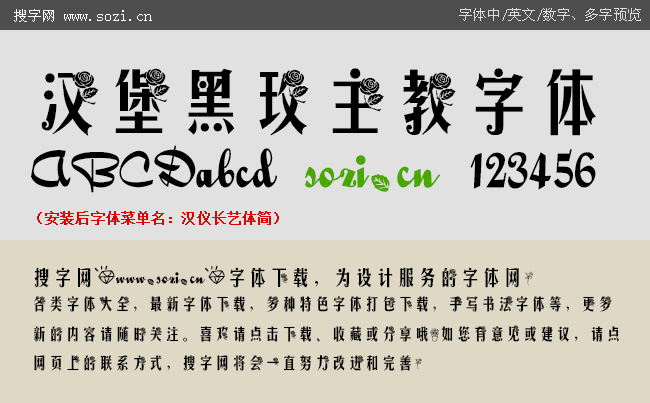
漢堡黑玫主教字體
搜字網給大家提供一款漢堡黑玫主教字體手機中文字體下載。這款手機字體是在漢儀長藝體筆畫間插入了漂亮的玫瑰花圖案。筆畫既有黑體的粗壯醒目,又有宋體的秀美柔和,加上藝術性的圓球形點、起筆如蝌蚪形的頓點、螺螄轉似的小鉤,配以修長的字形,如少女般婷婷玉立,裊娜動人,美觀而不落俗套。加入了卡通圖案后又增添了藝術性,特別適合喜歡手機字體個性一些的朋友在手機上安裝使用。